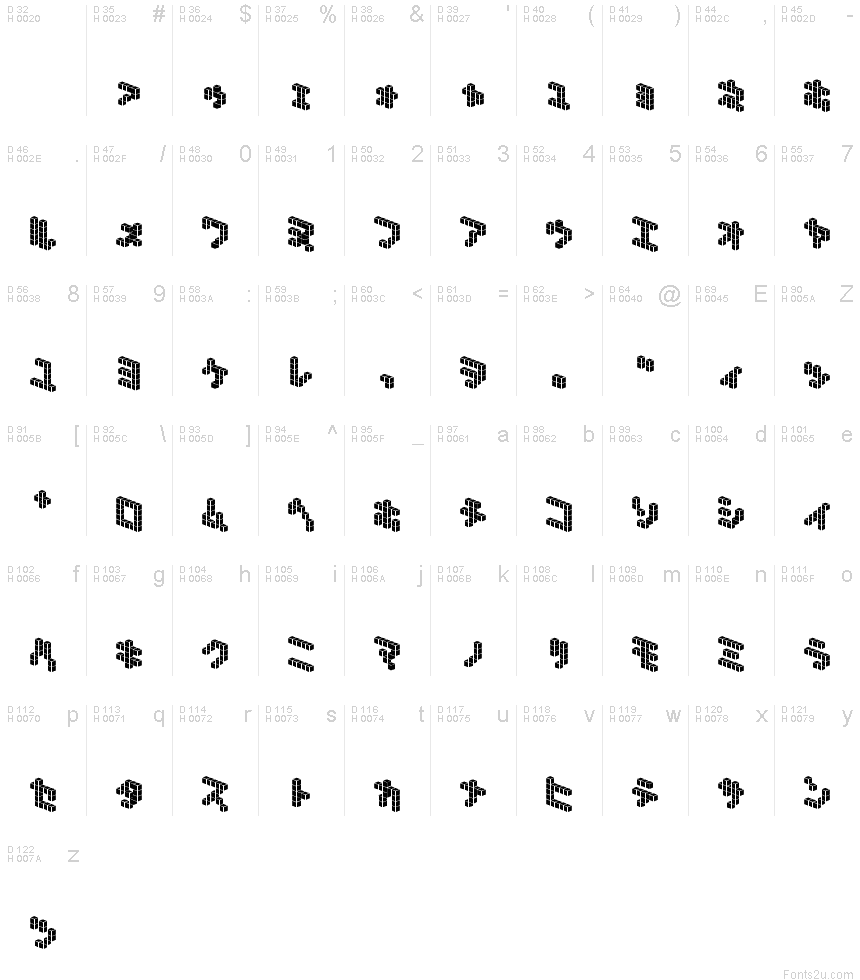
DemonCubicBlock NKP Tile
خط Demon Cubic Block NKP Tile font هو خط ياباني مجاني ثلاثي الأبعاد، يحول كل كلمة إلى متاهة نيون صغيرة. تمنحه شبكات المكعبات الضخمة والظلال المتدرجة ملمساً حاداً يشبه ألعاب الآركيد القديمة، وكأن الحروف منحوتة من وحدات بكسل متراصة. وبفضل تباعد حروفه الضيق وتكرار أشكال المكعبات، يضفي خط Demon Cubic Block NKP طاقة سيبرانية نابضة، وكأنه مأخوذ مباشرة من أجهزة الألعاب الكلاسيكية أو من لافتات النيون المتلألئة في أزقة طوكيو.
استخدم خط Demon Cubic Block NKP Tile font لإضفاء طابع تقني فوري على عناوين الألعاب، وتصاميم البث المباشر، وملصقات الفعاليات، وعناوين المنشورات، والملصقات المطبوعة، ومجلات الخيال العلمي. يبرز هذا الخط المجاني بوضوح عند استخدامه بحجم كبير وعريض، حيث تبقى بنية المكعبات ثلاثية الأبعاد حادة وواضحة. بالنسبة للنصوص الأساسية، نسقه مع خط هندسي بسيط بلا زوائد لضمان القراءة السهلة، بينما تترك الحروف المكعبة المستوحاة من الطراز الياباني تخطف الأنظار.